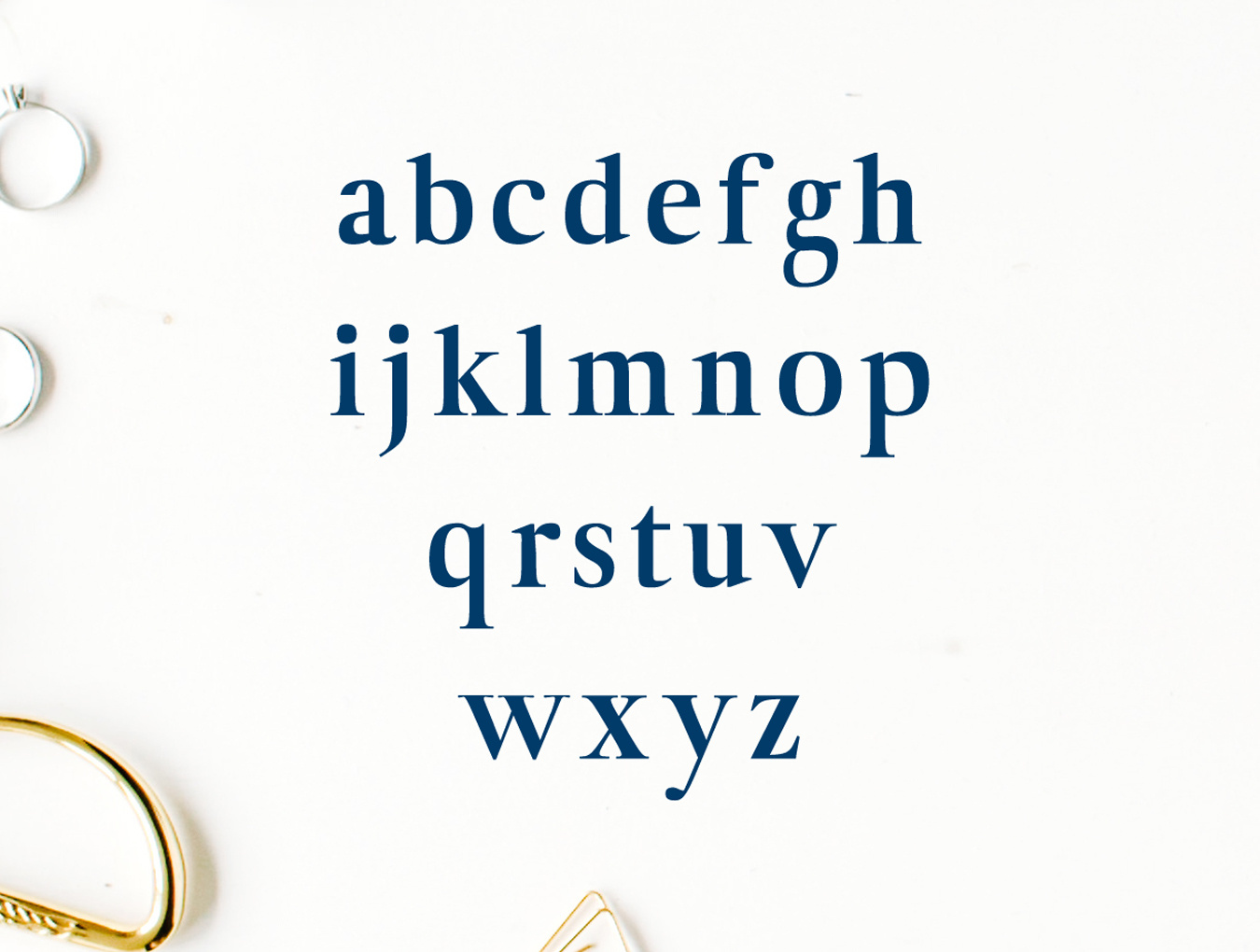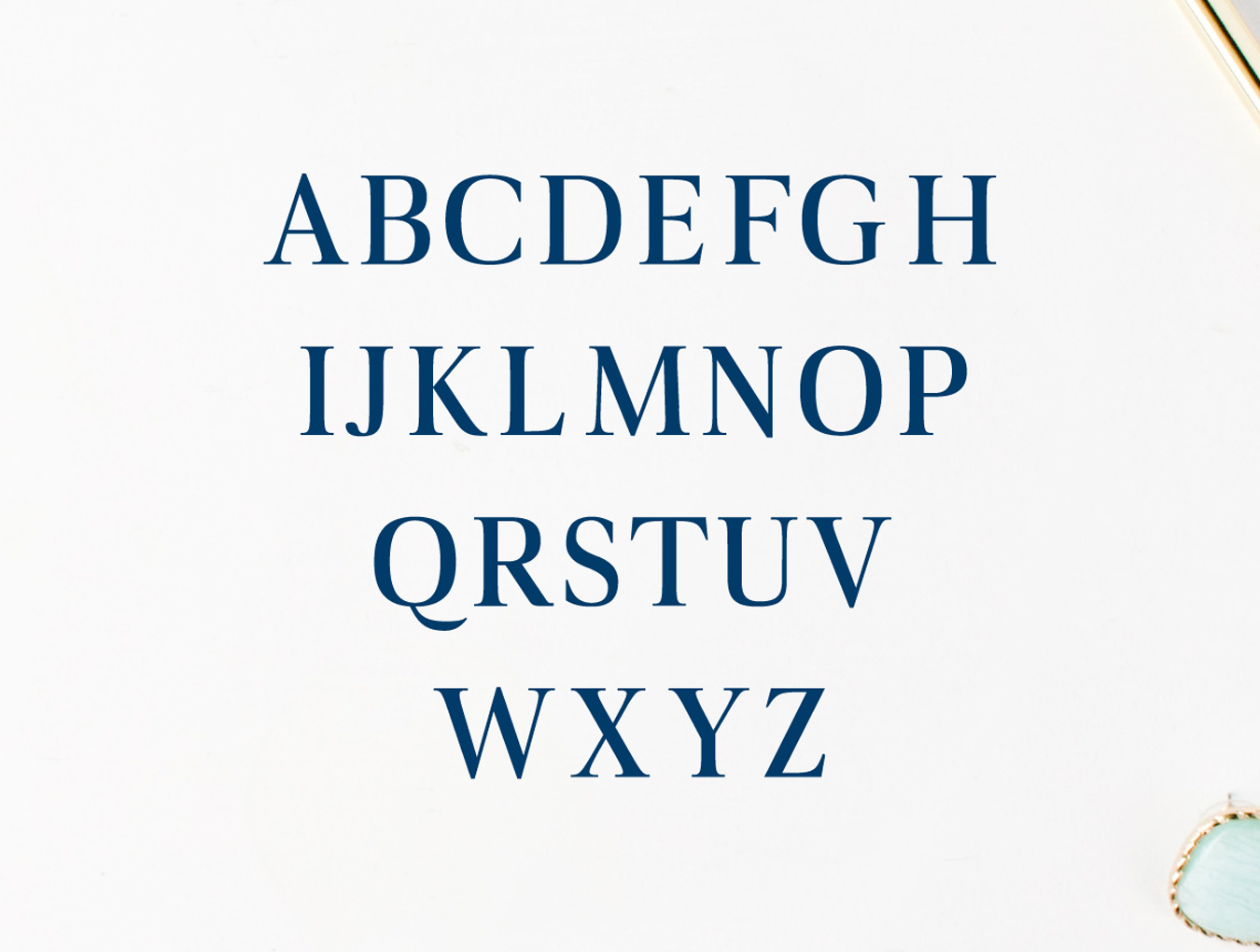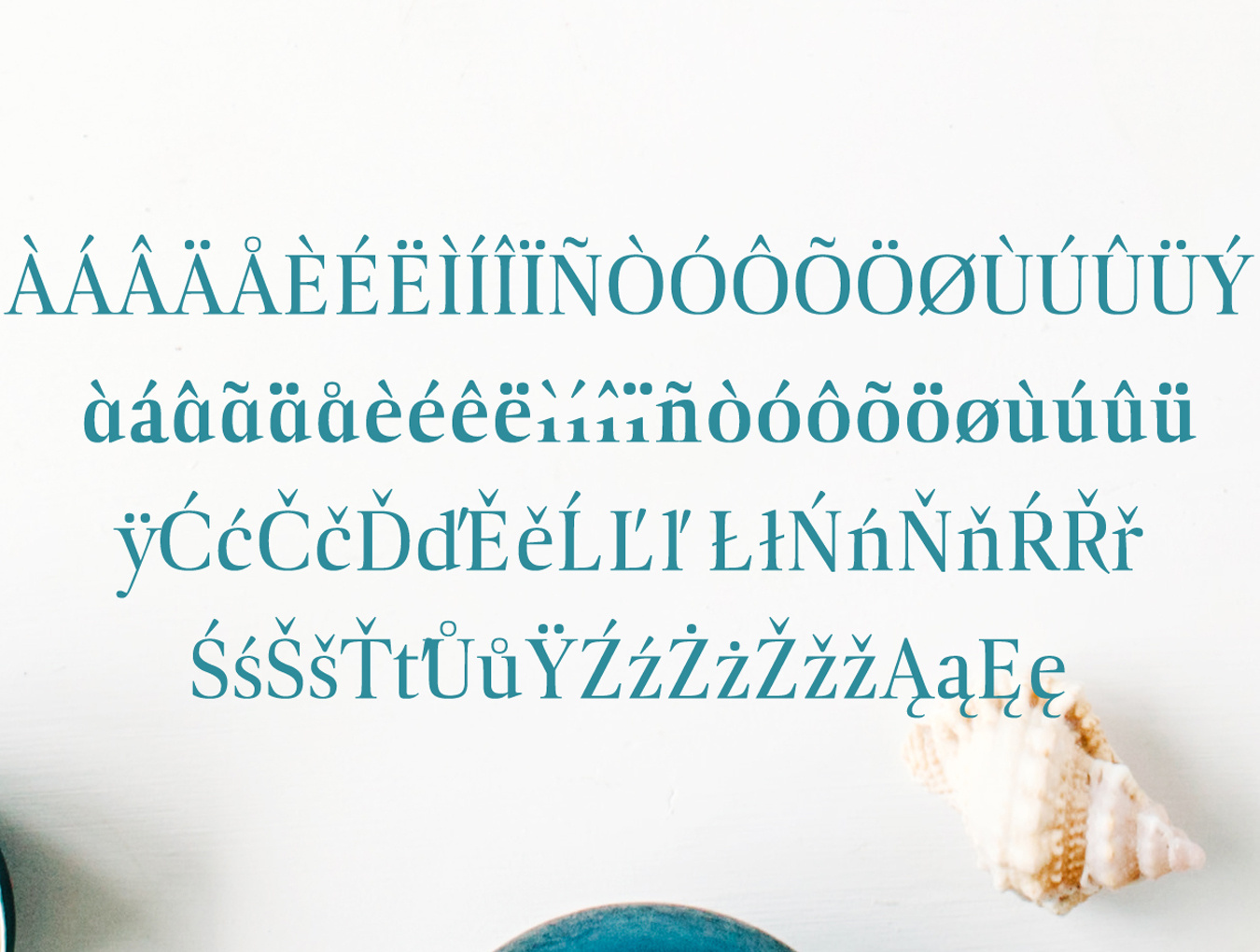
Carra Serif 2字体家庭装,Carra Serif字体
Carra Serif 2 Fonts Family Pack, Carra Serif Typeface
Carra Serif字体是一个最小的干净衬线字体系列,包含3个重量,它具有独特和现代的衬线外观和感觉。非常适合华丽的徽标,标题,网页布局和品牌。如果你想尝试一个优雅的外观,它看起来华丽,所有帽子都有宽大的间距,或者在大写字母和小写字母中完美无瑕。